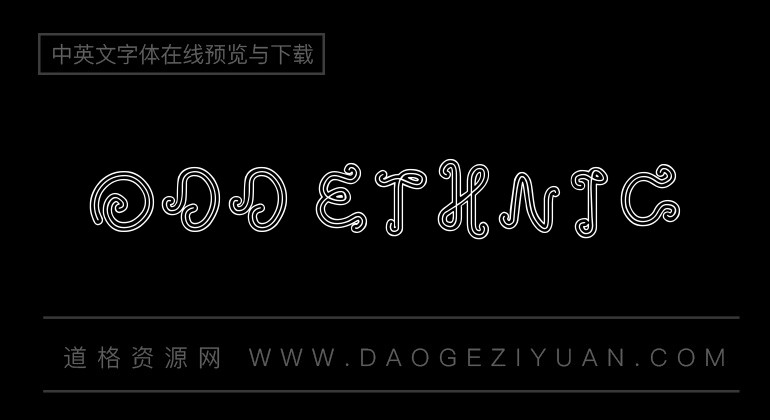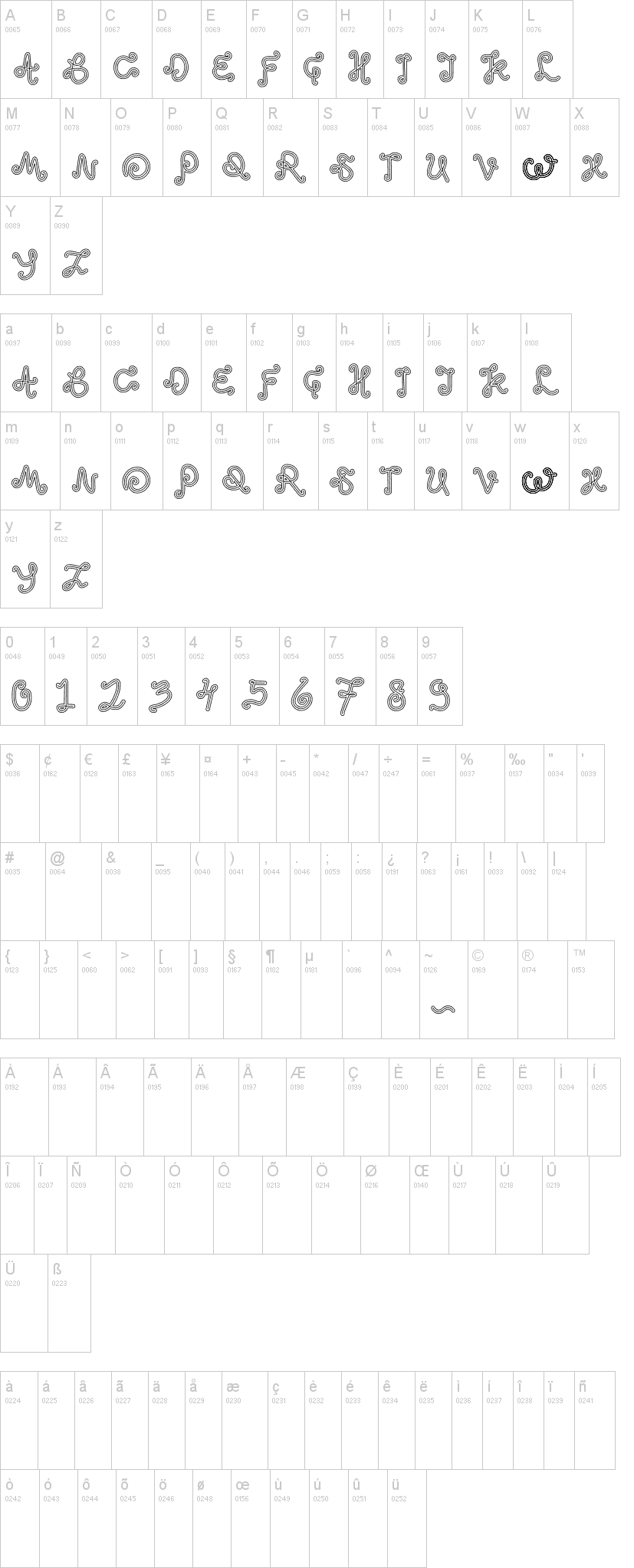
? Odd Ethnic 字体是一款具有独特设计风格的复古英文字体,它采用了明显的古典设计元素,使用更加复古的字体样式来表现出古老的文字,具有细节丰富的外观。它具有清晰的文字表现,可以用于各种复古风格的设计,如品牌标识、海报、T恤等。内容介绍
Odd Ethnic是一款非常不错的手写艺术字体,具有很好的视觉感,适合于文化类的宣传设计、商业类品牌的广告和产品包装设计以及个性化文字排版等较多场景。